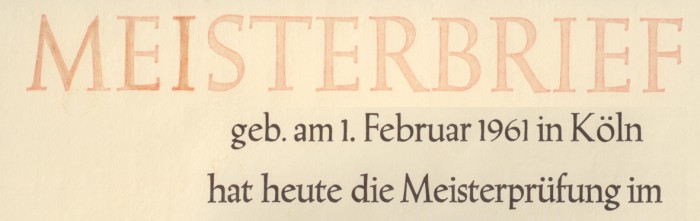
Wie heißt diese Schrift?
Vielen Dank. Gibt es eine ähnliche lizenzfreie Schrift, bei der das "M" an den Seiten schräg steht?
Wirf ev. auch mal einen Blick auf die Romantha (Downloadquelle hier, etwa in der Mitte der Seite), diese trägt den Namen nur aus rechtlichen Gründen und entspricht der Marathon von Rudolf Koch.
Eine kostenlose Version der Weiss-Antiqua findet sich im früher kommerziell vertriebenen, aber 2009 freigegebenen Qualitype-Schriftenpaket unter QTWeise. Es gibt darin sogar drei Schriftschnitte Regular, Bold und Italic.
Hast Du (über den angefragten Font hinaus) Erfahrungen mit dem Paket, taugt das was?
OK, der Volksmund sagt nicht zu Unrecht »einem geschenkten Barsch schaut man nicht ins Maul«, aber die Qualität bei freien Fonts variiert doch so gewaltig, dass mich vor Download, Durchsicht und Ausprobieren Deine Meinung interessieren würde.
Dem Sammlertrieb folgend habe ich das Schriftenpaket zwar schon eine Weile auf der Platte, real genutzt habe ich es allerdings noch nicht. Da das Paket ursprünglich von 1992 stammt und 2009 wohl nur noch mit der Opentype-Kerning-Funktion versehen wurde enthalten die Schriften kein Eurozeichen. Umlaute und kleines Eszett sind aber vorhanden.
Viele der Schriftarten sind auch im Corelpaket enthalten. Die Qualität wie ich sie hier so am Rechner beurteilen kann ist halbwegs akzeptabel. Es gibt aber auch Grausamkeiten wie die fetten Schnitte der QTTechton (Tekton) nicht nur, daß die Knuppel am Strichende fehlen, was man vielleicht noch hinnehmen könnte, die Linienführung hat auch noch kleinere Dellen. Interessant sind ev. noch die zwei Schnitte der QTEraType, welche der heute wohl nicht mehr erhältlichen aufrecht stehenden Eras entspricht.